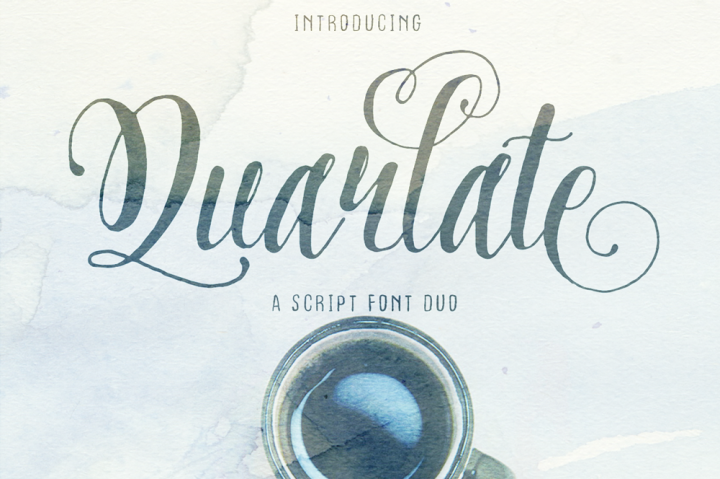
Quarlate Font Duo – Download Grátis
Quarlate é uma combinação perfeita de dois tipos de fontes para designers que buscam elementos naturais e modernos para seus projetos. Esta dupla de script fontes, idealmente combinada, oferece um equilíbrio fascinante entre uma elegante e ondulante tipografia casual e uma escrita divertida feita à mão. A combinação única é perfeita tanto quando usadas juntas quanto individualmente – você tem acesso a ambos os estilos em cada design. Esta fonte universal expandirá sua coleção de tipos de texto, permitindo-lhe criar designs carinhosos e descontraídos ou dar uma aparência sofisticada e elegante para seu trabalho. Quarlate é uma ótima escolha tanto para designers que procuram um toque pessoal em seus projetos quanto para aqueles que desejam agregar ao design de marcas, sem sacrificar a personalidade. Quando você descarrega a Quarlate Font Duo, está adquirindo duas fontes únicas e distintas que não apenas expandem seu acervo, mas também o aprimoram. Este é um investimento valioso para qualquer designer gráfico, oferecendo um conjunto de opções incríveis para criar texturas variadas em uma variedade de cenários.